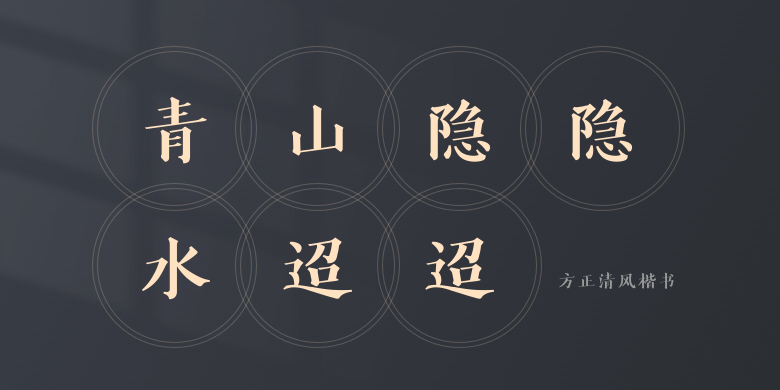
方正清风楷书
方正清风楷书,这款字体结构工整、笔画清晰,兼顾美观与易读性,适用于标题、正文、海报、包装、LOGO 等多种场景。字形优雅稳定,风格百搭耐看,适配日常排版与创意设计,让文字呈现更舒适、更具质感。方正清风楷书一笔一画,皆是细节,以均衡的比例、流畅的线条打造舒适视觉体验,字形端正大气,风格简约现代。无论是商业设计、品牌宣传还是日常排版,都能轻松驾驭,让文字更有格调与力量。方正清风楷书字体下载。